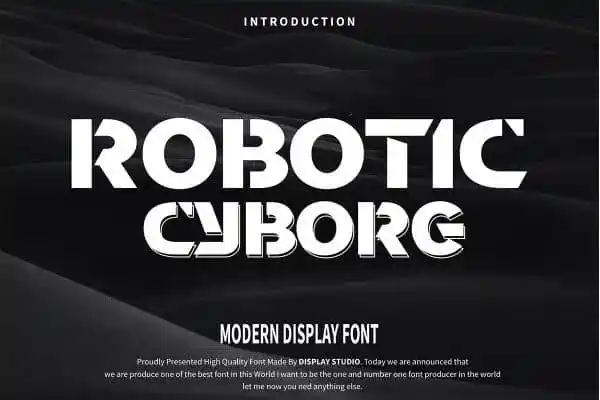
Robotic Cyborg Display Font – Download Grátis
Robotic Cyborg Display Font é uma tipografia geométrica contemporânea que combina a estrutura clara dos caracteres com linhas sólidas e diretas, criando um visual futurista e moderno. Perfeita para designers buscando um estilo único, esta fonte traz um toque de tecnologia aos projetos editoriais, branding ou infográficos, destacando o trabalho da sua maneira única. Ideal tanto para revistas fashion, como para peças publicitárias digitais e design gráfico moderno, a Robotic Cyborg Display Font é uma ótima opção para designers que desejam imprimir identidade visual com estilo em seus projetos.